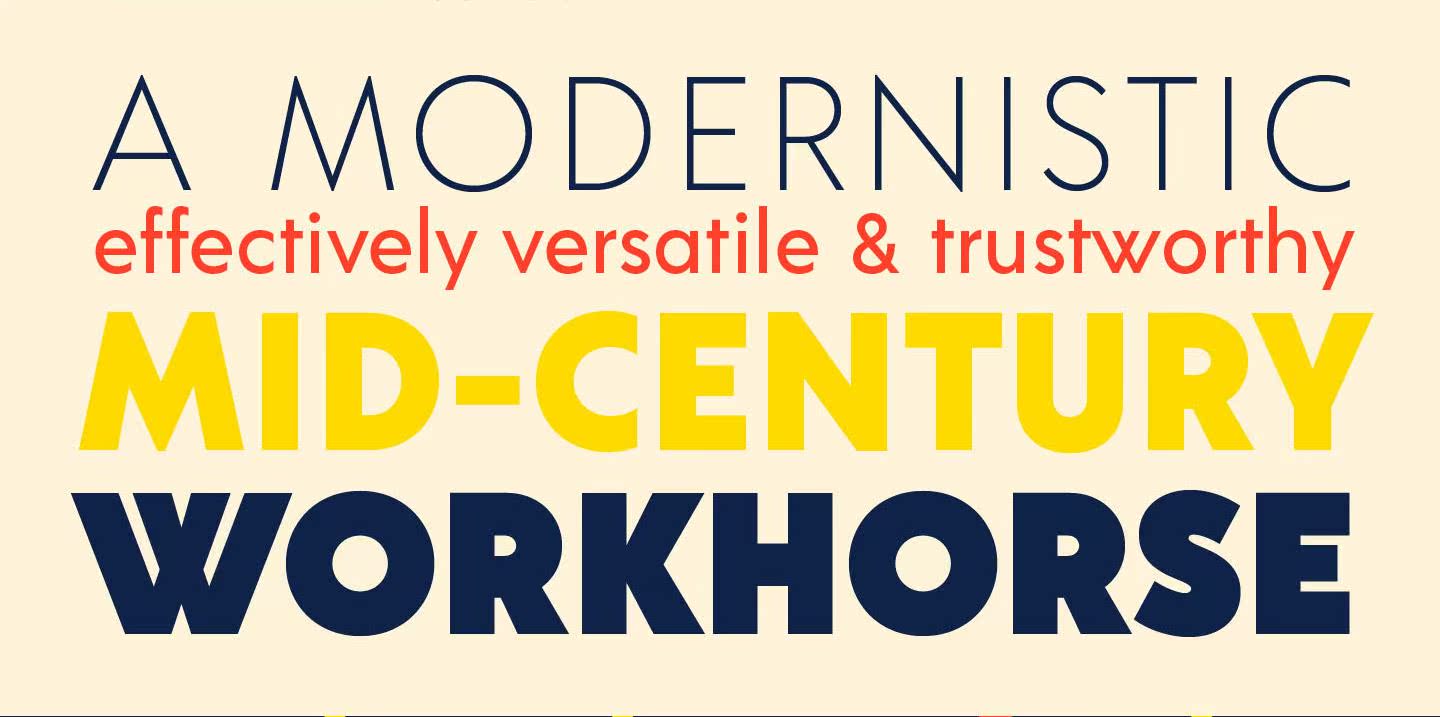
AcretypeFace Free Weights是一个由八种二十种字体组成的几何系列的一部分。它由作者的祖父TexAcre提出并命名。TexAcre是一个标准的标志制造商,他制作的标志照亮了美国中西部的道路。Acretrics是他的作品,而且许多模板都支持20世纪早期的几何图形。从黑色到黑色的距离为8/2,此演示文稿具有极大的通用性,可用于显示、文本或两者之间的任何内容。AcreOffers Full European Language支持表格和旧样式图形等多种开放式功能。